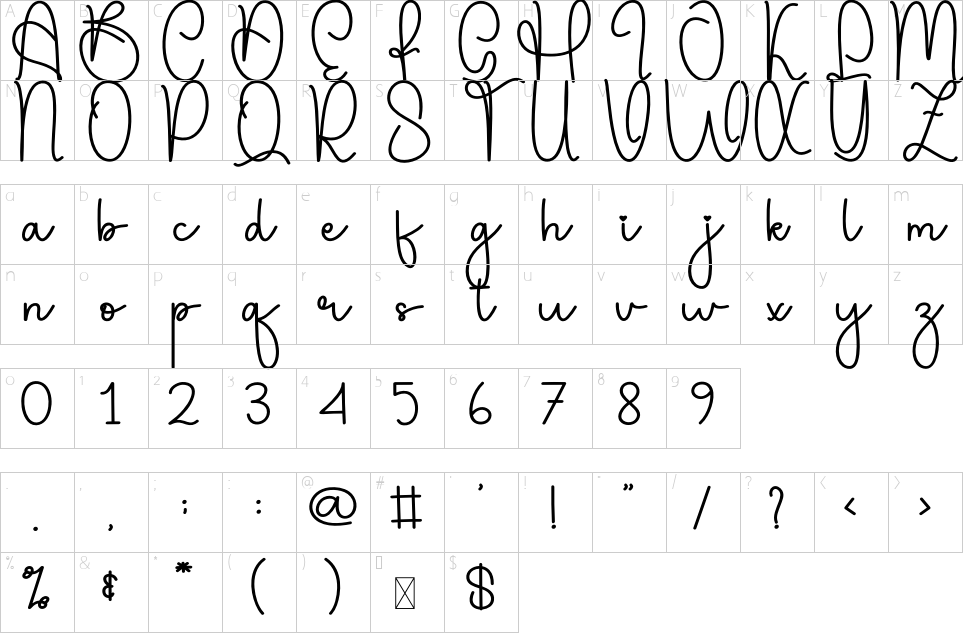
A Santa Vibes Font é uma opção incrível para aqueles que desejam adicionar um toque vibrante e único aos seus projetos digitais. Esta fonte, projetada por ninguém menos que o talentoso William Jhordy, é perfeita para criar textos vibrantes e coloridos. Disponível tanto para Windows quanto para Mac, a Santa Vibes traz vida e energia para qualquer design. Com 268 downloads, é evidente que designers e criadores de conteúdo estão encantados com a facilidade de uso e a versatilidade desta fonte. Seja para criar layouts interessantes, artigos de estilo, ou apenas para adicionar um toque especial a qualquer projeto, a Santa Vibes font é um recurso gráfico imperdível.